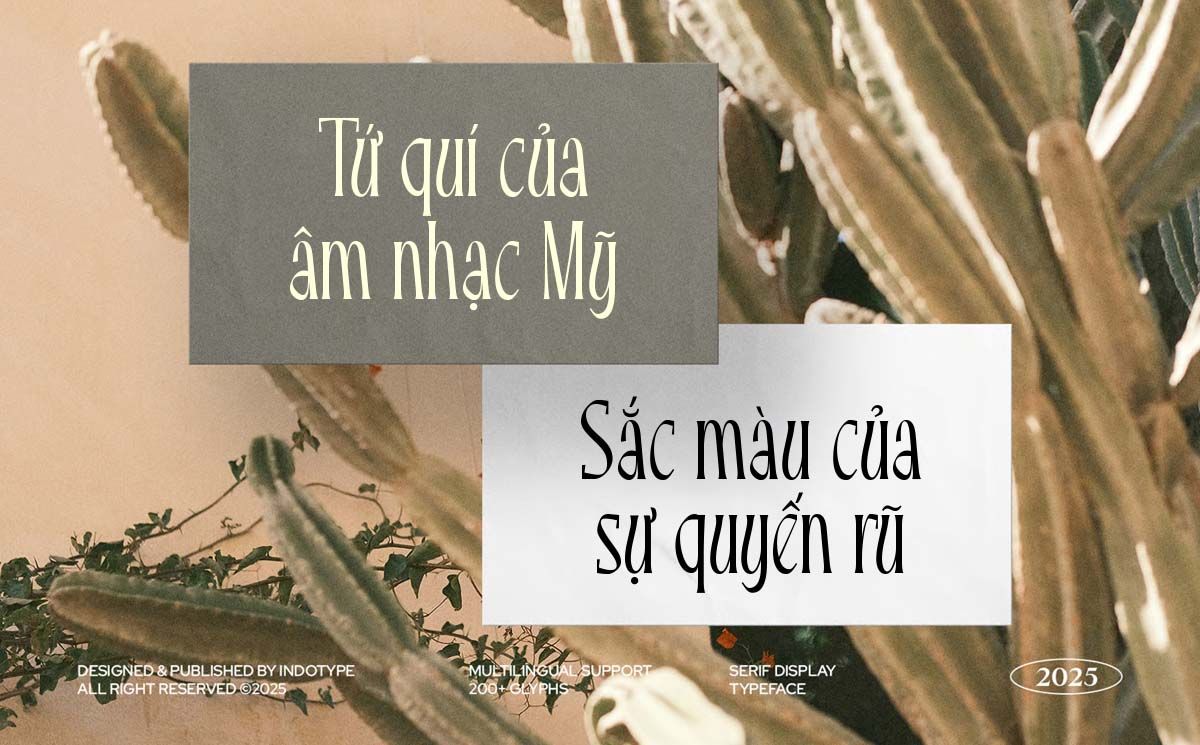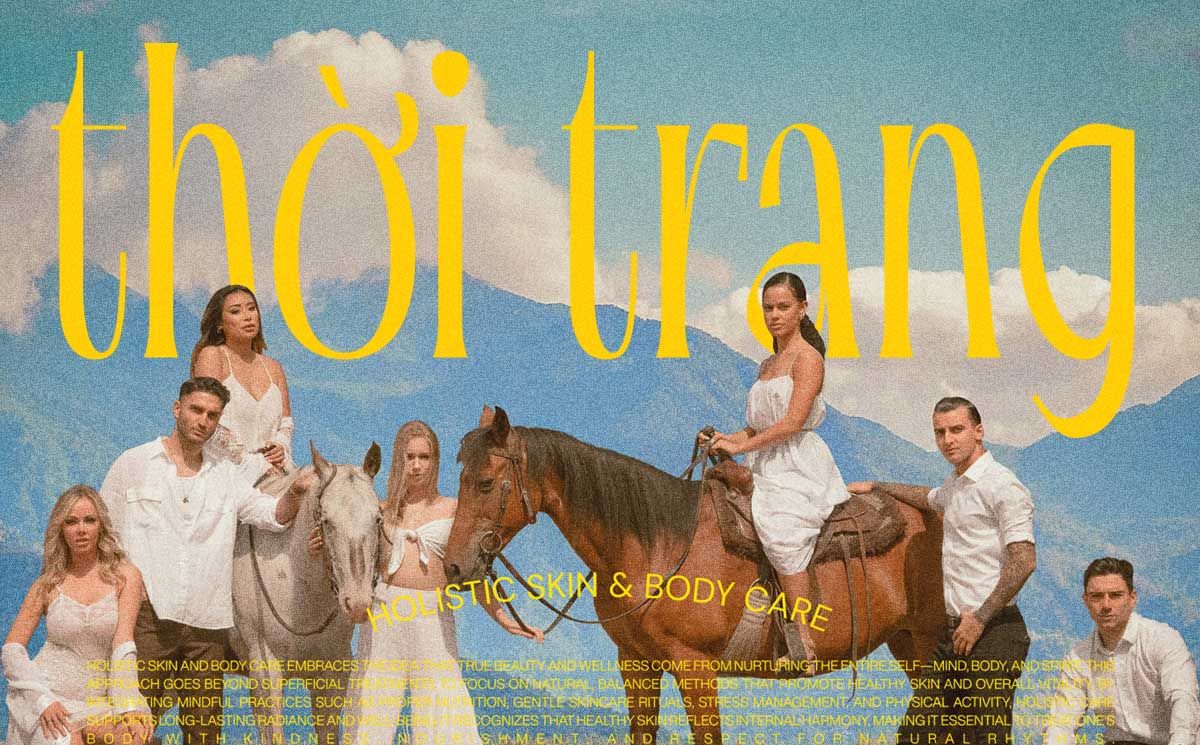
Wrigskan vốn nổi bật với phong cách serif cao cấp, sang trọng và đầy tinh tế. Các ký tự được thiết kế với tỷ lệ thanh mảnh, phần chân (serif) mềm mại nhưng sắc sảo, tạo nên sự cân bằng hoàn hảo giữa cổ điển và hiện đại. Font hỗ trợ hơn 350 glyphs cùng hệ thống ligature đặc biệt, giúp việc ghép nối chữ trở nên độc đáo, nghệ thuật hơn. Nhờ vậy, Wrigskan Regular nhanh chóng trở thành lựa chọn yêu thích trong các dự án thiết kế logo thương hiệu, bìa tạp chí, bao bì mỹ phẩm, wedding card hay ấn phẩm quảng cáo cao cấp.
Khi được Việt hóa và đổi tên thành TH Wrigskan, font không chỉ giữ nguyên vẻ đẹp nguyên bản mà còn được tối ưu để sử dụng mượt mà trong tiếng Việt. Các dấu thanh, dấu mũ, dấu móc được chỉnh sửa tinh tế, bảo đảm hài hòa với tổng thể kiểu chữ, mang lại trải nghiệm thị giác hoàn hảo. Đây là bước cải tiến quan trọng, giúp các nhà thiết kế tại Việt Nam có thêm công cụ mạnh mẽ để sáng tạo mà không lo lỗi font hay mất đi tính thẩm mỹ.
Ứng dụng thực tế, TH Wrigskan phù hợp với các dự án branding đòi hỏi sự tinh tế và sang trọng. Dù là thiết kế poster nghệ thuật, bộ nhận diện thương hiệu, bao bì cao cấp hay các sản phẩm in ấn thời trang, font này đều giúp tôn lên sự khác biệt, chuyên nghiệp và đẳng cấp.
Nếu bạn đang tìm kiếm một font chữ sang trọng, font luxury, font serif hiện đại với đầy đủ hỗ trợ tiếng Việt, thì TH Wrigskan chính là sự lựa chọn hoàn hảo để nâng tầm thiết kế.